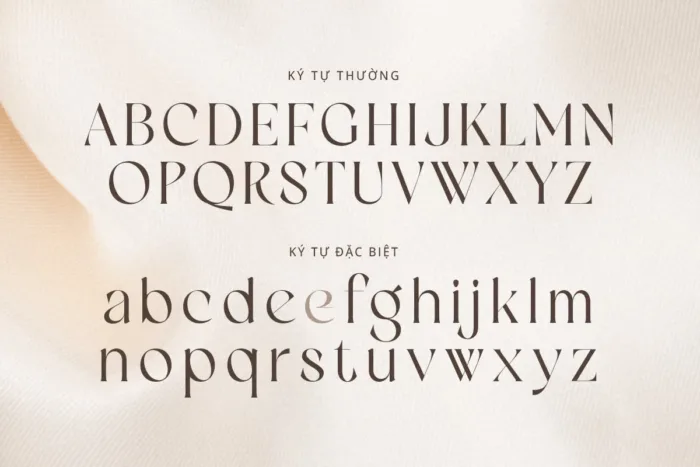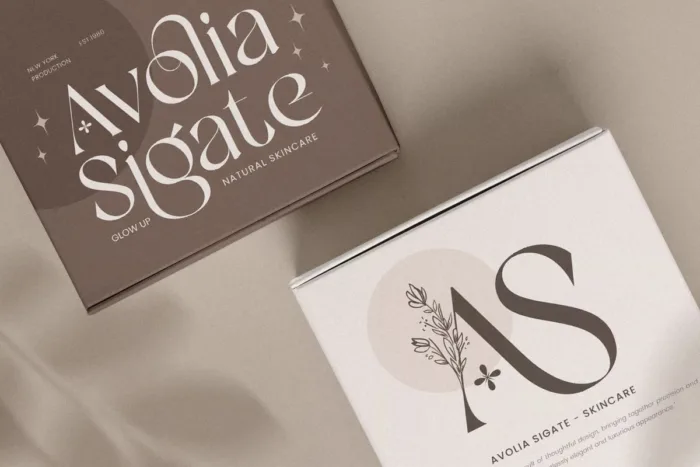
DVN Qiolany Việt hóa – Font chữ Serif phong cách sang trọng
DVN Qiolany là một font chữ mang phong cách sang trọng, hiện đại với sự kết hợp tinh tế giữa serif truyền thống và những đường nét cách điệu độc đáo. Bộ chữ mang lại cảm giác thanh lịch với các ký tự có độ dày mỏng xen kẽ, tạo hiệu ứng thị giác thu hút. Điểm nhấn của DVN Qiolany nằm ở những đường cắt tinh tế và các chi tiết cong nhẹ, giúp bộ font trở nên mềm mại nhưng vẫn giữ được sự mạnh mẽ và chuyên nghiệp.
Font này phù hợp để sử dụng trong thiết kế thương hiệu cao cấp, thời trang, mỹ phẩm, bìa sách, thiệp mời hoặc các dự án cần đến sự tinh tế và nghệ thuật. DVN Qiolany hỗ trợ đầy đủ bảng chữ cái viết hoa và viết thường, mang đến sự linh hoạt trong thiết kế. Nếu bạn đang tìm kiếm một font chữ vừa sang trọng vừa cá tính, DVN Qiolany sẽ là lựa chọn hoàn hảo.